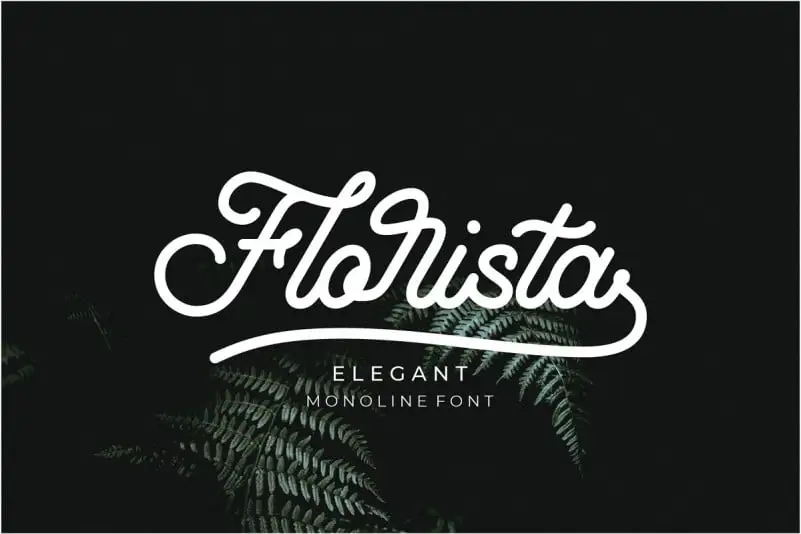
A Florista Script Font é uma elegante fonte monoline criada para designers amadores e profissionais que buscam estilizar seus projetos de design. Com caracteres fluindo de maneira natural, essa fonte proporciona um toque único aos textos mais interessantes para diversos tipos de aplicação. A Florista Script é uma fonte script com acabamento limpo e agradável ao olho, desenvolvida para adaptar-se em qualquer projeto design. Esta fonte abrange alternativas, ligaturas, alternâncias contextualizadas e desenhos finalizados da ligatura (type ‘s1’, ‘s2’ e ‘s3’). Uma excelente opção tanto para logotipos quanto para identidades visuais, identidade corporativa, selos, roupas, panfletos e muito mais. Seja você um designer profissional ou iniciante, a Florista Script é uma fonte perfeita para tornar seus projetos de design ainda mais especializados.